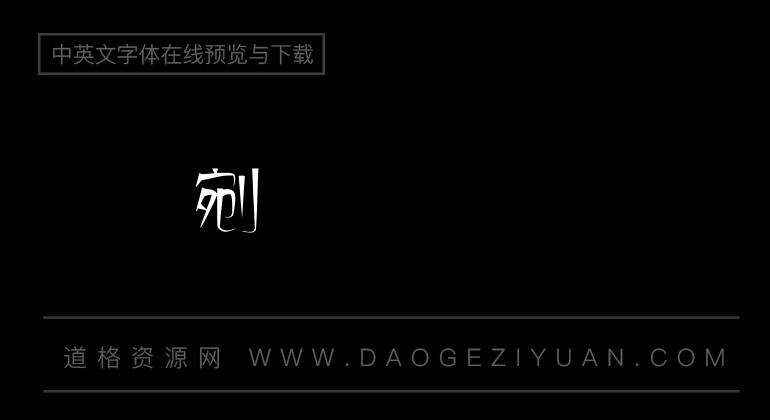
金梅美术工艺字体
金梅美术工艺字体是一款由金梅文化艺术设计团队设计的艺术字体,它的特点是结合了传统的中国绘画艺术风格,将艺术与字体完美结合,把字体设计变得更加精致,充满艺术气息。金梅美术工艺字体的字形设计源自中国传统的绘画艺术,在设计上采用了折衷的风格,把现代设计技术与中国传统文化融合在一起,使字体更加美观大方,充满艺术气息。
金梅美术工艺字体是一款非常不错的手写艺术字体,具有很好的视觉感,适合于文化类的宣传设计、商业类品牌的广告和产品包装设计以及个性化文字排版等较多场景。